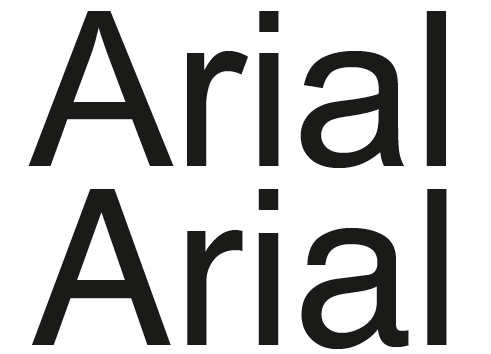
Hmm. Hat Jemand mal die Ariel mit der Helvetica verglichen ?
Keinen einzigen Unterschied festgestellt ?
Und ? Klingelts schon ?
URL machte es sich noch einfacher:
Dort nennt sich die Futura "Futurex",
die Times "Timex" und so weiter.
Scheinbar alles ganz einfach :-)
Hmm. Hat Jemand mal die Ariel mit der Helvetica verglichen ?
Keinen einzigen Unterschied festgestellt ? Und ? Klingelts schon ?
ring-ring ...
Natürlich sind das beides statische Grotesk-Schriften. Aber genauso haben auch Mercedes, BMW und Lexus Nobel-Limousinen im Angebot, die zwar alle den selben Zweck erfüllen, aber trotzdem ist jede anders.
URL machte es sich noch einfacher: Dort nennt sich die Futura "Futurex", die Times "Timex" und so weiter. Scheinbar alles ganz einfach :-)
Ich kenn die Schriften nicht bzw. finde auch nichts dazu – aber es könnte auch andere Gründe haben: Schriftformen inzwischen frei, Markenname aber noch nicht. Was noch nicht heißt, dass "URL" eine bestehende Font-Datei einfach umbenannt hat.
Natürlich sind das beides statische Grotesk-Schriften. Aber genauso haben auch Mercedes, BMW und Lexus Nobel-Limousinen im Angebot, die zwar alle den selben Zweck erfüllen, aber trotzdem ist jede anders.
"Natürlich" sind beide Schriften Ein und das Selbe.
Namen sind Schall und Rauch, wusste Herr Goethe bereits.
Nenne die Ariel in Helvetica um und gebe der Helvetica den Namen Ariel und NICHTS hat sich verändert. (Fontographer machts möglich)
Ich kannte mal nen Kollegen, der kaufte die "Neue Helvetica".
Er zahlte dafür schlappe 1.200 Märker.
Ja, das waren noch Zeiten :-)
Mit Verlaub, du redest ziemlichen Stuss. :schonklar: